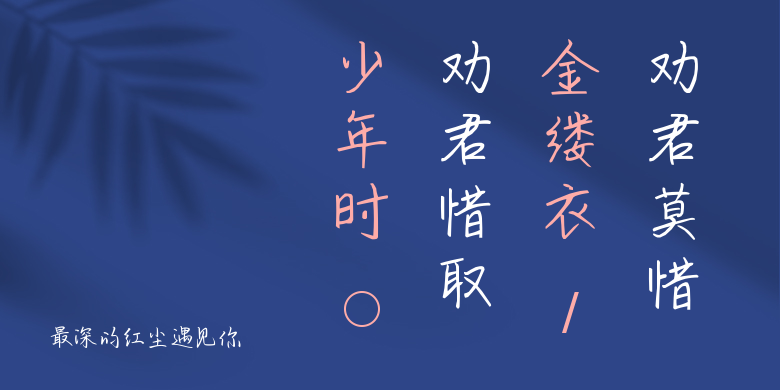
最深的红尘遇见你
最深的红尘遇见你,这款字体结构工整、笔画清晰,兼顾美观与易读性,适用于标题、正文、海报、包装、LOGO 等多种场景。字形优雅稳定,风格百搭耐看,适配日常排版与创意设计,让文字呈现更舒适、更具质感。最深的红尘遇见你一笔一画,皆是细节,以均衡的比例、流畅的线条打造舒适视觉体验,字形端正大气,风格简约现代。无论是商业设计、品牌宣传还是日常排版,都能轻松驾驭,让文字更有格调与力量。最深的红尘遇见你字体下载。